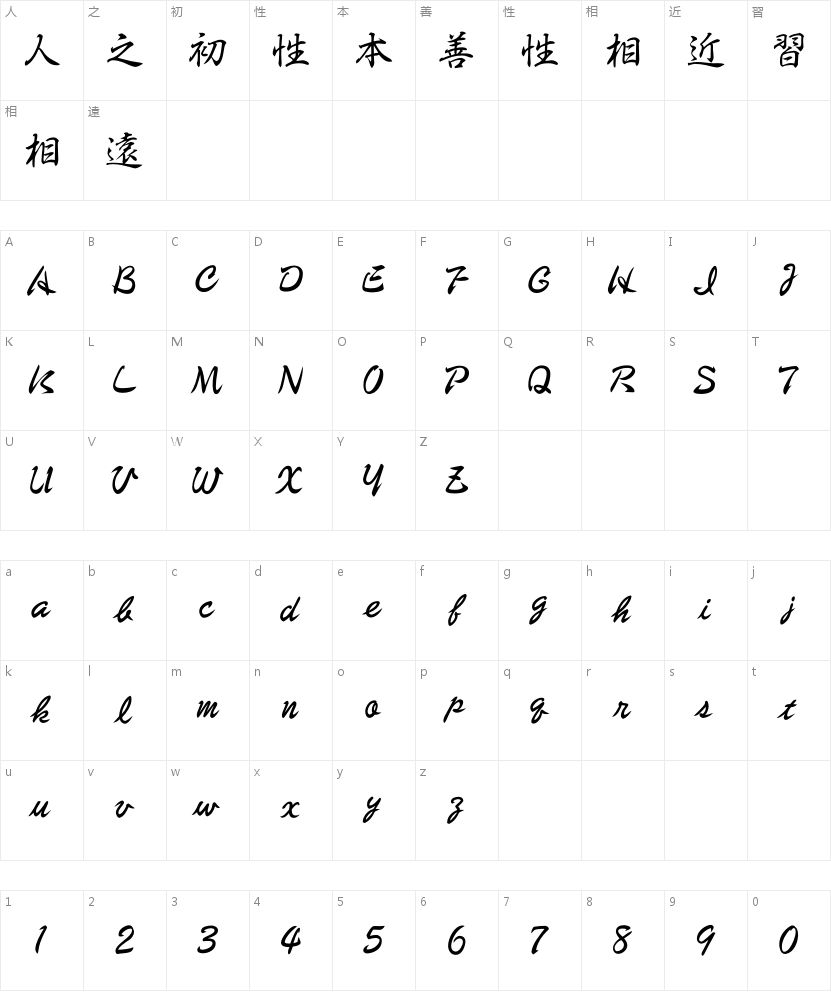
? HOT-白舟行書 Std R 字体是一款繁体中文字体,由台湾白舟文化创作发行。字体以清新活泼的繁体中文字体,为您带来更具有特色的文字效果,拥有较高的可读性,适合用于文章、报纸、书籍、广告等文字排版。字体拥有良好的结构设计,具有良好的字形细节,使用时可以更舒适地阅读,给读者带来更好的视觉体验。文件名:HOT-GyoshoStd-R-2.otf
HOT-白舟行書 Std R是一款非常不错的手写艺术字体,具有很好的视觉感,适合于文化类的宣传设计、商业类品牌的广告和产品包装设计以及个性化文字排版等较多场景。